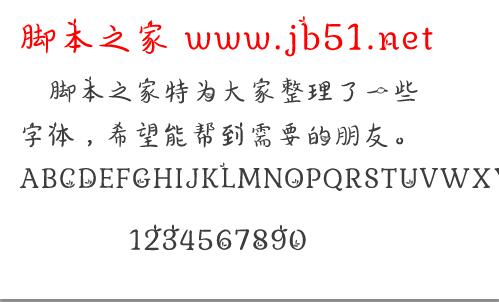
Aa檸檬小姐字體是一款應(yīng)用于藝術(shù)設(shè)計(jì)方面的簡(jiǎn)體中文字體,該字體線條粗細(xì)適中,字形結(jié)構(gòu)明朗,并帶有小草的花紋,整體效果非常出色,并且字庫(kù)完整,能夠適用于美術(shù)設(shè)計(jì)、廣告設(shè)計(jì)、宣傳海報(bào)、ppt、影視制作以及任何使用文字的領(lǐng)域,有需要的朋友可以免費(fèi)下載收藏。